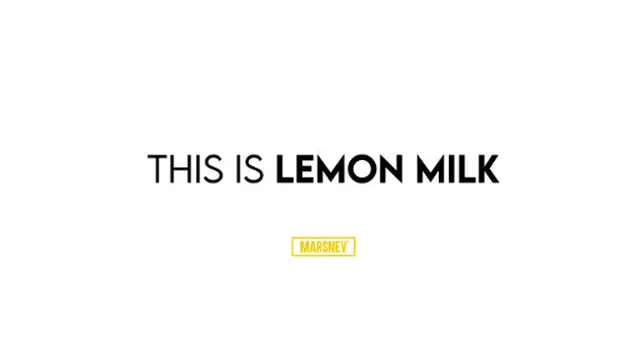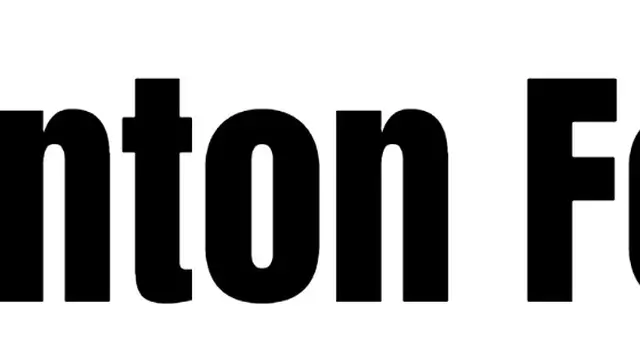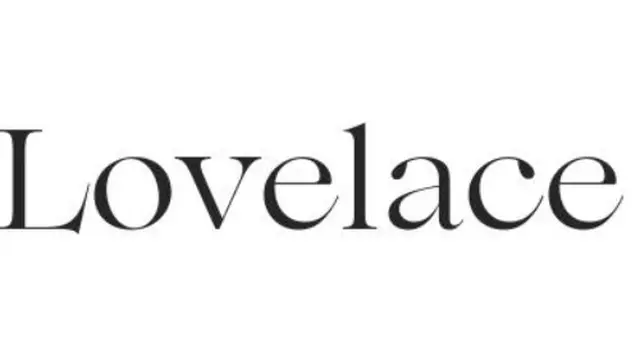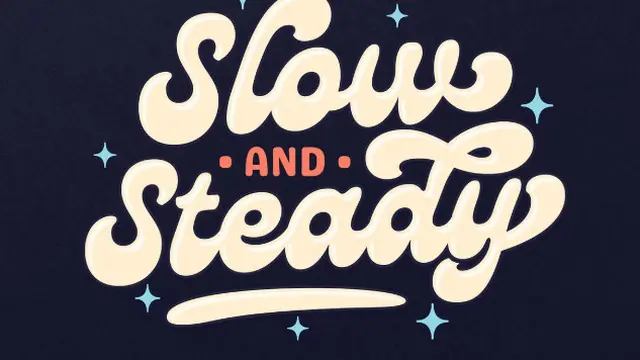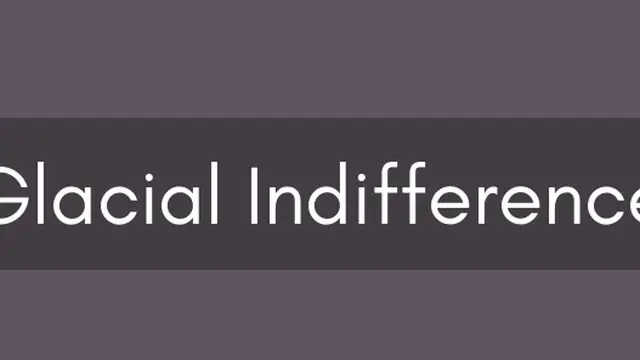
Liputan6.com, Jakarta Di 2025, tampilan visual yang menarik dan segar menjadi salah satu kunci kesuksesan sebuah desain, baik untuk media sosial, presentasi, maupun branding bisnis. Salah satu elemen penting yang memengaruhi kesan sebuah desain adalah pemilihan font. Di Canva, tersedia ratusan pilihan font yang bisa membuat karya Anda tidak terlihat monoton atau kaku.
Dengan menggunakan rekomendasi font Canva yang tepat, desain pun jadi lebih hidup dan mampu menyampaikan pesan dengan lebih efektif. Banyak pengguna Canva, baik pemula maupun profesional, seringkali masih menggunakan font-font default seperti Arial atau Times New Roman yang cenderung membosankan.
Padahal, Canva telah menyediakan beragam font unik dan kekinian yang bisa langsung digunakan tanpa perlu instalasi tambahan. Rekomendasi font Canva tersebut mulai dari gaya retro, modern, minimalis, hingga eksperimental, semua bisa ditemukan dalam platform ini. Memilih rekomendasi font Canva yang sesuai dengan tema dan nuansa desain akan meningkatkan daya tarik visual sekaligus memperkuat identitas merek Anda.
Berikut ini Liputan6.com ulas selengkapnya mengenai rekomendasi font Canva, Senin (5/5/2025).
1. Font Genty
Genty menjadi salah satu rekomendasi font Canva yang sedang naik daun di tahun 2025. Font ini memiliki karakter playful dengan goresan yang dinamis namun tetap terbaca dengan jelas. Tampilan hurufnya memberikan kesan santai, cocok digunakan untuk desain anak muda dan promosi produk lifestyle.
Desain font Genty memadukan elemen artistik dengan struktur huruf yang tidak kaku. Hal ini membuatnya banyak digunakan untuk kebutuhan desain poster, story Instagram, dan kemasan produk handmade. Warna cerah dan background polos sangat serasi dipadukan dengan Genty agar tetap fokus pada teks.
Meskipun terkesan kasual, Genty tetap mampu menciptakan kesan profesional bila diatur dengan komposisi yang tepat. Kombinasinya dengan elemen desain lain seperti ilustrasi atau shape geometris juga memperkuat tampilannya. Bagi kamu yang ingin membuat brand terlihat lebih ramah dan fun, font ini patut dicoba.
2. Font Tan Mon Cheri
Tan Mon Cheri adalah font serif modern yang memiliki nuansa klasik namun tetap kekinian. Gaya huruf ini menggabungkan detail feminin dengan ketegasan garis, membuatnya cocok untuk branding fashion, wedding invitation, dan kartu ucapan eksklusif.
Ciri khas dari Tan Mon Cheri terletak pada bentuk huruf kapital yang melengkung elegan. Meskipun merupakan font serif, tampilannya tidak kaku berkat ornamen lembut di setiap ujung hurufnya. Efek ini membuat font terlihat mewah tanpa harus berlebihan dalam desain.
Tan Mon Cheri sangat ideal digunakan sebagai judul utama atau headline dalam desain. Untuk hasil maksimal, pasangkan font ini dengan background soft atau pastel, serta hindari terlalu banyak elemen agar font menjadi pusat perhatian. Desainer pemula pun bisa memanfaatkannya untuk menciptakan desain yang terlihat premium.
3. Font Glacial Indifference
Bagi kamu yang menyukai gaya minimalis, Glacial Indifference adalah pilihan tepat. Rekomendasi font Canva sans-serif ini menawarkan kesan bersih, modern, dan netral, sehingga cocok digunakan untuk berbagai jenis desain.
Font ini sangat sering digunakan dalam desain presentasi, CV kreatif, maupun desain editorial. Bentuk hurufnya tegak lurus dan konsisten, memberi kesan profesional tanpa kehilangan daya tarik visual. Saat digunakan dalam ukuran besar, font ini sangat mudah terbaca.
Selain tampilan yang bersih, Glacial Indifference juga fleksibel untuk dipadukan dengan elemen desain lainnya. Kamu bisa mengombinasikannya dengan font script atau serif untuk menciptakan kontras yang menarik. Dengan penataan spasi dan warna yang tepat, font ini bisa membawa desainmu tampak berkelas dan modern.
4. Font Lemon Milk
Lemon Milk dikenal sebagai salah satu rekomendasi font Canva yang memiliki karakter kuat dan futuristik. Tampilan hurufnya yang tegas membuat font ini cocok digunakan untuk desain bertema teknologi, gaming, hingga event promosi yang energik.
Font ini memiliki struktur geometris dengan proporsi huruf yang seimbang. Meski terlihat berani, Lemon Milk tetap nyaman dibaca pada berbagai ukuran. Hal ini menjadikannya pilihan favorit untuk membuat poster, logo, dan banner digital.